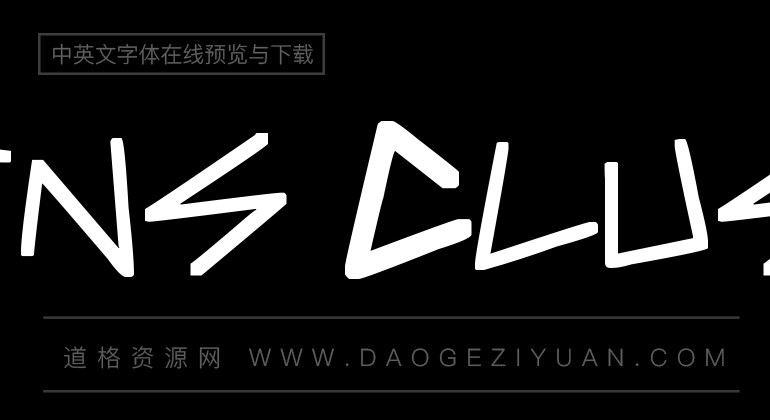
Incopins Clusters 是一款专为设计师和印刷专业人士设计的字体,它具有独特的折叠设计,可以帮助设计师和印刷专业人士更轻松地设计出更丰富多彩的字体。Incopins Clusters 字体拥有丰富的折叠设计,可以帮助设计师和印刷专业人士更轻松地设计出更丰富多彩的字体,从而让印刷作品更加生动有趣。此外,它还拥有多种字体样式,可以满足不同的设计需求。内容介绍
Incopins Clusters是一款非常不错的手写艺术字体,具有很好的视觉感,适合于文化类的宣传设计、商业类品牌的广告和产品包装设计以及个性化文字排版等较多场景。